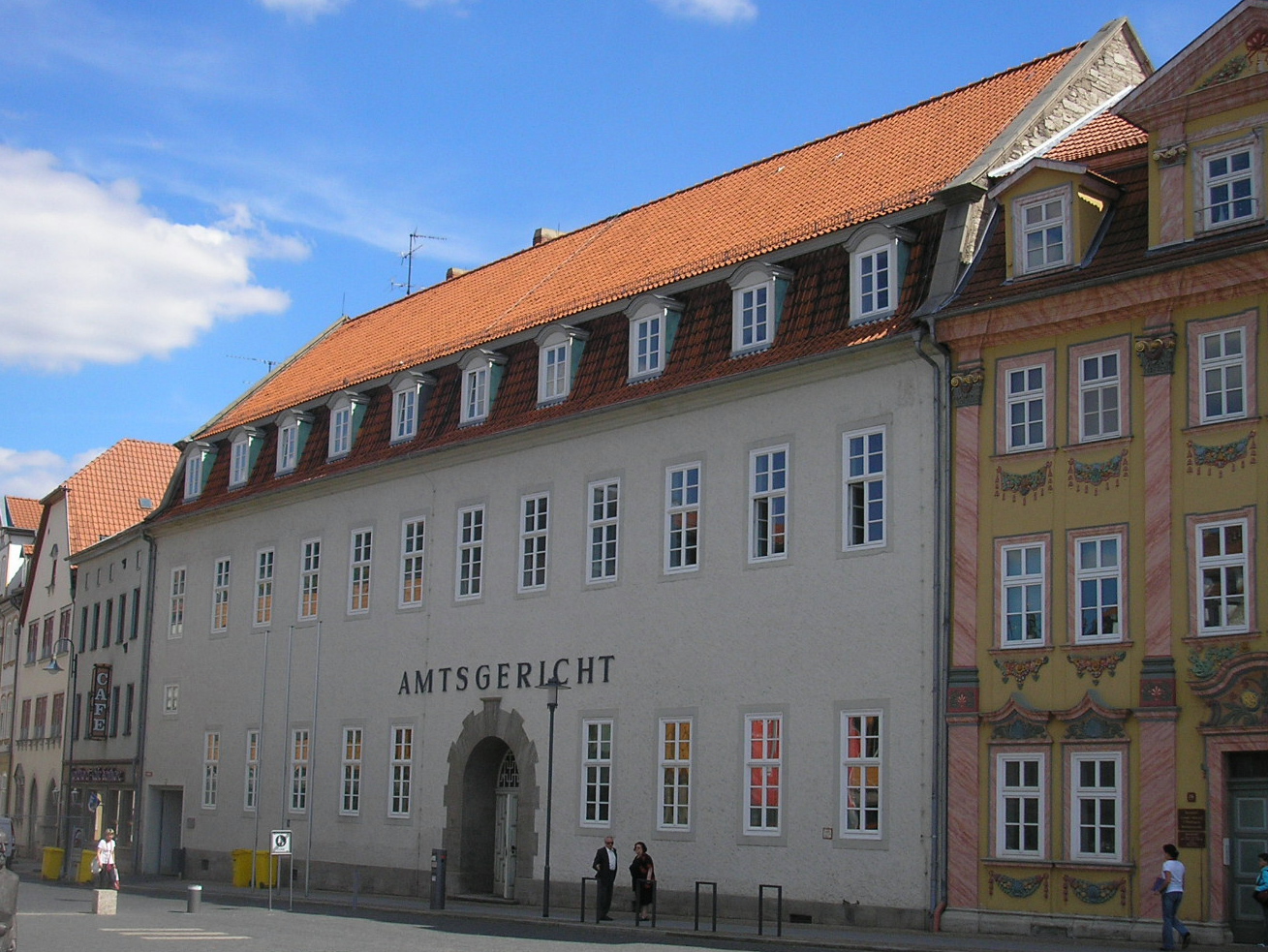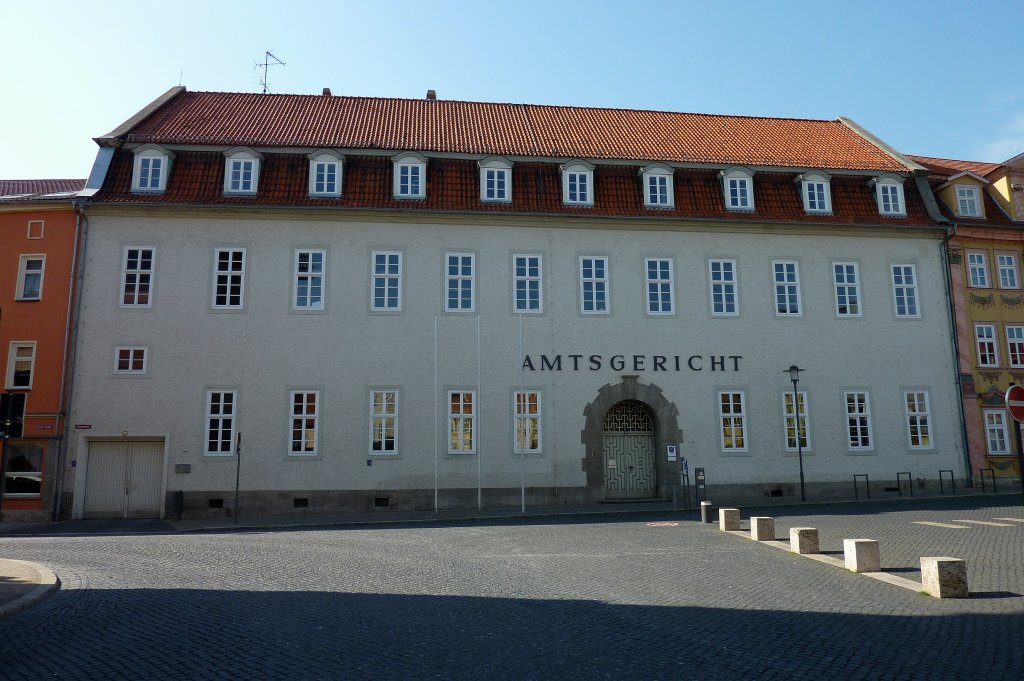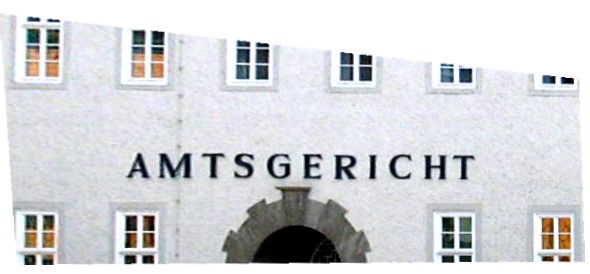
Schrift gesucht! (Amtsgericht)
vielleicht kann mir jemand bei der Suche dieser Schrift behilflich sein. Es handelt sich um den Schriftzug über dem Eingang des Amtsgericht Mühlhausen. Ziel ist es diese Typo im Zuge einer Sanierung bei der Beschilderung wieder zu verwenden. Vielen Dank im Vorraus!
pro-tipp: das posten eines (möglichst unverzerrten) bildes von deinem schriftbeispiel steigert deine chancen, eine gute antwort zu bekommen exponentiell!
Das einfachste wäre, den Schriftzug zu vermessen, die Buchstaben abzunehmen, diese aufzubereiten und wieder zu montieren.
Und selbst ein perspektivisch verzerrtes Bild ist 100 mal besser als eine reine Beschreibung, denn es gibt gute Software, die so etwas entzerren kann. :
CDas einfachste wäre, den Schriftzug zu vermessen, die Buchstaben abzunehmen, diese aufzubereiten und wieder zu montieren.
Bzw. die vermessenen/abgenommenen Buchstaben von einem Profi digitalisieren lassen und davon neue anfertigen.
Die Buchstaben dürften so oder so Handarbeit sein und es wird sich also keine direkte Entsprechung als Schrift finden lassen.
Auf solch eine Art ist ja auch meine Postamt entstanden: http://www.peter-wiegel.de/Postamt.html
Hier ist jemand, als gerade ein Gerüst stand, zu den Buchstaben geklettert, und hat diese auf Papier abgerieben, dazu dann noch Maße notiert. Damit lässt sich dann leicht eine Schrift erstellen, die dann auch gut um weitere Buchstaben ergänzt werden kann, auch wenn es von den fehlenden nur unscharfe Fotos gibt. Ziel war hier das vor langer Zeit abgenommene "Kaiserliches" wieder zu ergänzen, nachdem das Gebäude eben kein offizielles Postamt mehr war.